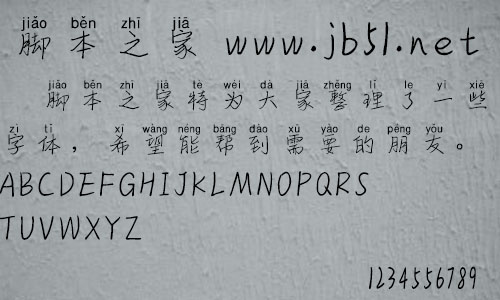
漢儀夢(mèng)里隨風(fēng)搖曳簡(jiǎn)一款不錯(cuò)的藝術(shù)字體,由漢儀字庫(kù)出品,字體筆觸纖細(xì),字形端正,具有很好的視覺(jué)感,適合應(yīng)用于藝術(shù)設(shè)計(jì)、平面宣傳設(shè)計(jì)、網(wǎng)頁(yè)設(shè)計(jì),書(shū)法字帖等領(lǐng)域,需要的朋友可以前來(lái)本站下載。